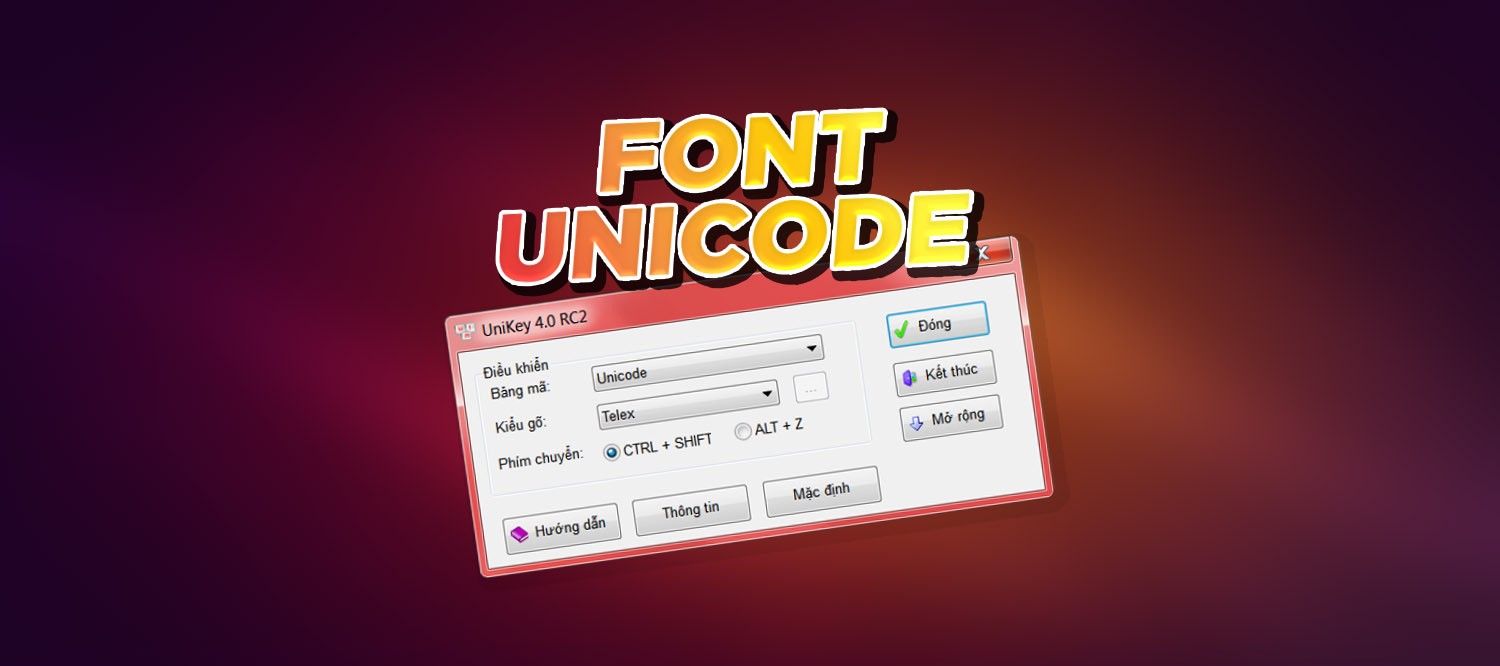
Font chữ Unicode ngày càng trở nên phổ biến vì khả năng hỗ trợ nhiều ngôn ngữ khác nhau, bao gồm cả tiếng Việt. Vậy, làm thế nào để tìm kiếm và sử dụng những font chữ Unicode miễn phí cho các dự án thiết kế của bạn? Bài viết này sẽ cung cấp thông tin chi tiết về các bộ font chữ Unicode miễn phí, cách tải xuống và ứng dụng chúng trong công việc thiết kế.
Unicode là một hệ thống mã hóa ký tự toàn cầu, được thiết kế để hỗ trợ hầu hết các ngôn ngữ và hệ thống chữ viết trên thế giới. Trái ngược với các chuẩn mã hóa trước đây như ASCII, chỉ hỗ trợ 128 ký tự, Unicode có thể mã hóa hơn 1 triệu ký tự, bao gồm cả những ký tự đặc biệt từ các ngôn ngữ khác nhau. Unicode sử dụng các điểm mã duy nhất cho mỗi ký tự, đảm bảo tính nhất quán và khả năng tương thích giữa các hệ thống và ứng dụng.
Mã hóa Unicode hoạt động bằng cách sử dụng ba hệ thống mã hóa chính: UTF-8, UTF-16 và UTF-32. UTF-8 linh hoạt, sử dụng từ 1 đến 4 byte để mã hóa ký tự, phù hợp với cả ASCII và các ký tự đa ngôn ngữ.
UTF-16 sử dụng 2 byte cho các ký tự từ U+0000 đến U+FFFF và 4 byte cho các ký tự khác. UTF-32, với 4 byte cho mỗi ký tự, hỗ trợ tất cả các ký tự trong chuẩn Unicode mà không cần đến cặp surrogate. Mỗi hệ thống mã hóa này đều giúp Unicode đạt được mục tiêu là xử lý và lưu trữ thông tin đa ngôn ngữ một cách hiệu quả trên nền tảng kỹ thuật số.
Font chữ Unicode là các font chữ được thiết kế để hỗ trợ bảng mã Unicode như đã nói ở trên. Khác với các font chữ truyền thống chỉ hỗ trợ một số ký tự nhất định, font chữ Unicode có thể bao gồm hàng triệu ký tự từ nhiều hệ thống chữ viết khác nhau, bao gồm cả các ngôn ngữ đặc biệt và chữ tượng hình.
Sử dụng font chữ Unicode trong thiết kế không chỉ giúp các dự án trở nên chuyên nghiệp và thống nhất mà còn giúp bạn dễ dàng chia sẻ và sử dụng nội dung trên nhiều nền tảng khác nhau mà không gặp phải vấn đề tương thích.
Bảng mã unicode gồm những font chữ nào? Bảng mã Unicode hiện nay hỗ trợ đến 172 font chữ khác nhau, được thiết kế để đáp ứng nhu cầu sử dụng đa dạng trong các hệ thống máy tính và phần mềm. Tuy nhiên, trong thực tế, không phải tất cả các font chữ này đều được sử dụng phổ biến. Dưới đây là một số font chữ thuộc bảng mã Unicode:
Arial, Comic Sans, Courier New, Palatino, Tahoma, Times New Roman, Trebuchet, Aachen, AGOldFace, Algerian, Amazon, AmericanUnc, Amherst, Arabia, Architecture, Arial-Rounded, Ariston, Arrus, AvantGarde, Aztek, BankGothic, Bodoni, Bookman, Brush Script, Casablanca, Cooper, Copperplate Gothic, Courier, Digital, Elephant, ErasContour, FetteFraktur, Frutiger, Futura, Garamond, GillSans, Goudy Old, Harrington, Helvetica, Hobo, Impact, Joanna, Kaufmann, Korinna, Lydian, Lucida Handwriting, Murray, News Gothic, Optima, Palatino, Rockwell, Serpentine, Snell, Times, Verdana, Windsor, ZapfChancery…
Để tiết kiệm thời gian và công sức trong việc tìm kiếm font chữ Unicode, bạn có thể tham khảo một số bộ font Unicode miễn phí dưới đây, mỗi bộ cung cấp một lượng font phong phú để lựa chọn cho dự án của bạn.
Bộ font UTM là một trong những bộ font phổ biến nhất đối với người thiết kế tại Việt Nam. Với hơn 150 font chữ, bộ này cung cấp nhiều lựa chọn cho các dự án thiết kế văn bản, logo, quảng cáo hay bất kỳ mục đích sử dụng nào. Các font của UTM đều hỗ trợ đầy đủ các ký tự tiếng Việt và có phong cách đa dạng, từ cổ điển đến hiện đại, phù hợp với nhiều nhu cầu thiết kế.
Bộ font SVN nổi bật với hơn 300 font chữ khác nhau. Đây là bộ font lý tưởng cho các nhà thiết kế đồ họa chuyên nghiệp, với các font chữ hỗ trợ đầy đủ các ngôn ngữ và đặc biệt là tiếng Việt. SVN cũng cung cấp nhiều phong cách khác nhau, từ serif đến sans-serif, giúp bạn dễ dàng tạo ra các thiết kế đa dạng và sáng tạo.
Bộ font UVN gồm 113 font chữ, có sẵn cho tải về miễn phí. Các font trong bộ UVN được thiết kế với nhiều kiểu dáng và đặc trưng, phù hợp với các dự án thiết kế cần sự đa dạng và mới mẻ. Font UVN là lựa chọn tuyệt vời cho các công trình thiết kế yêu cầu độ chi tiết cao và tính thẩm mỹ vượt trội.
Với 100 font chữ, bộ font Iciel tập trung vào các thiết kế có tính chất nghệ thuật và sáng tạo. Các font trong bộ Iciel đều mang lại cảm giác cổ điển nhưng cũng rất hiện đại, giúp bạn dễ dàng tạo ra những sản phẩm thiết kế đẹp mắt. Đây là bộ font không thể thiếu cho những ai yêu thích sự độc đáo và sáng tạo.
Bộ font TH là một bộ sưu tập phong phú với 400 font chữ. Bộ này cung cấp nhiều loại font khác nhau, từ font chữ truyền thống đến font chữ hiện đại, giúp bạn dễ dàng lựa chọn font phù hợp với yêu cầu dự án thiết kế. Bộ TH đặc biệt phù hợp với các công ty, tổ chức hoặc các nhà thiết kế cần một bộ font lớn và đa dạng để phục vụ cho nhiều mục đích khác nhau.